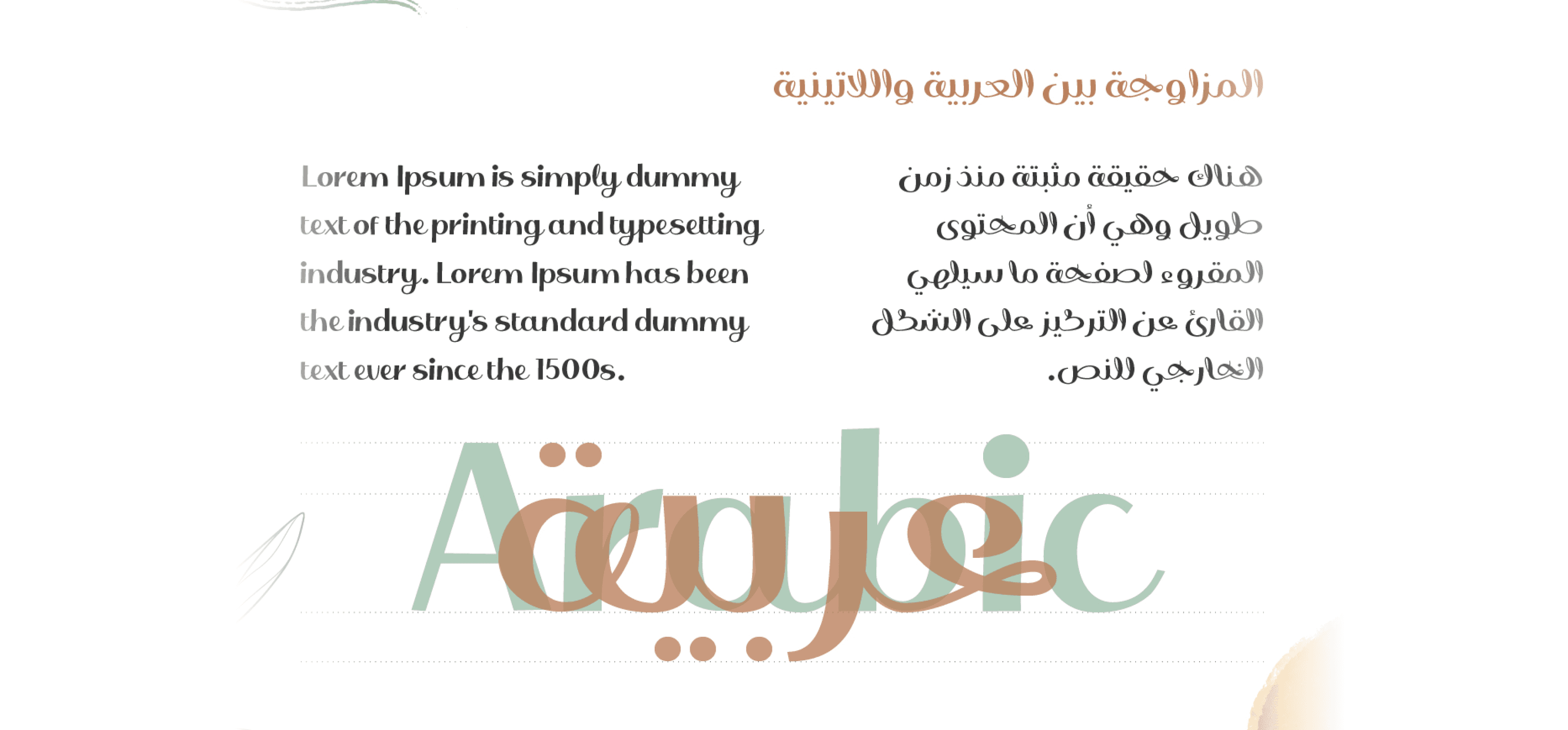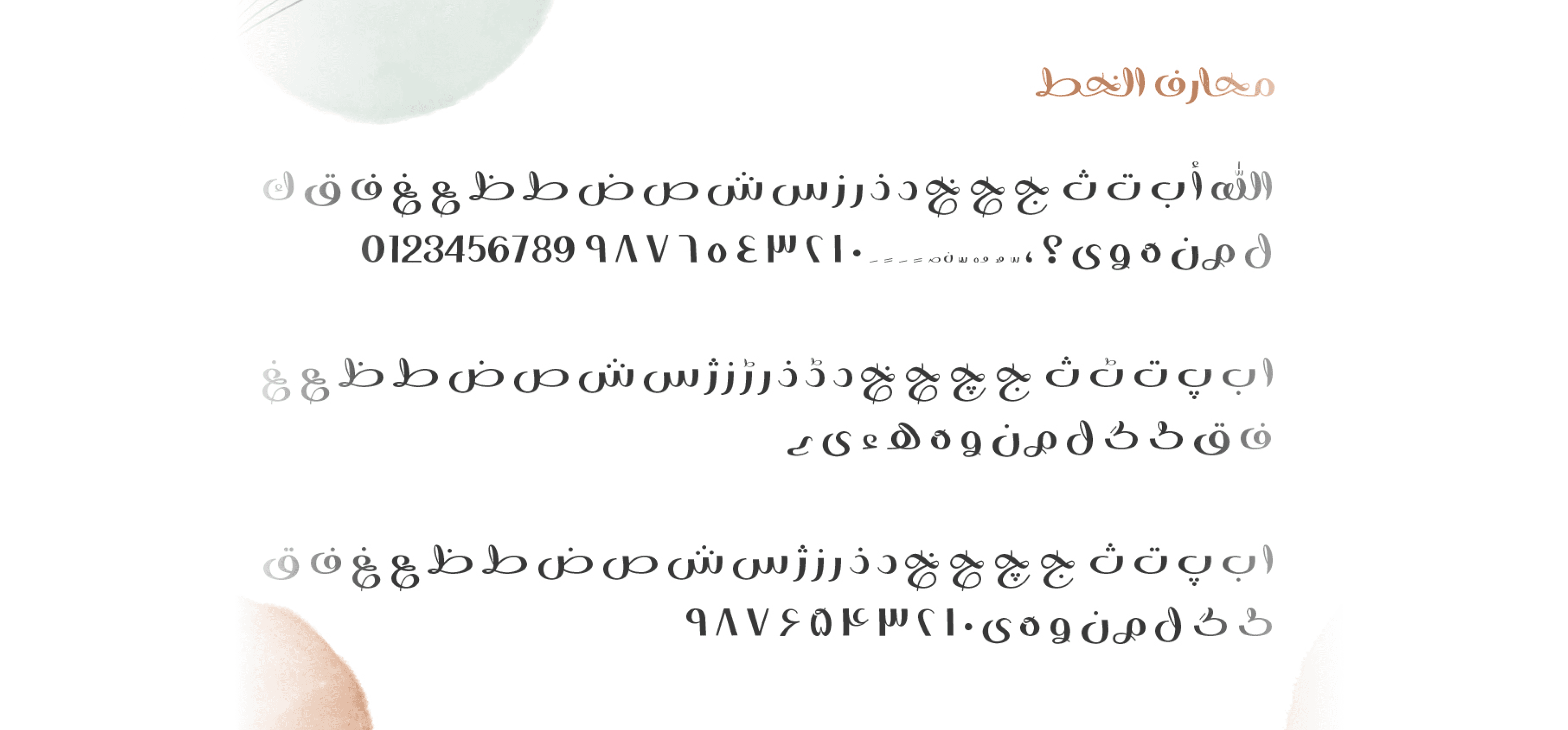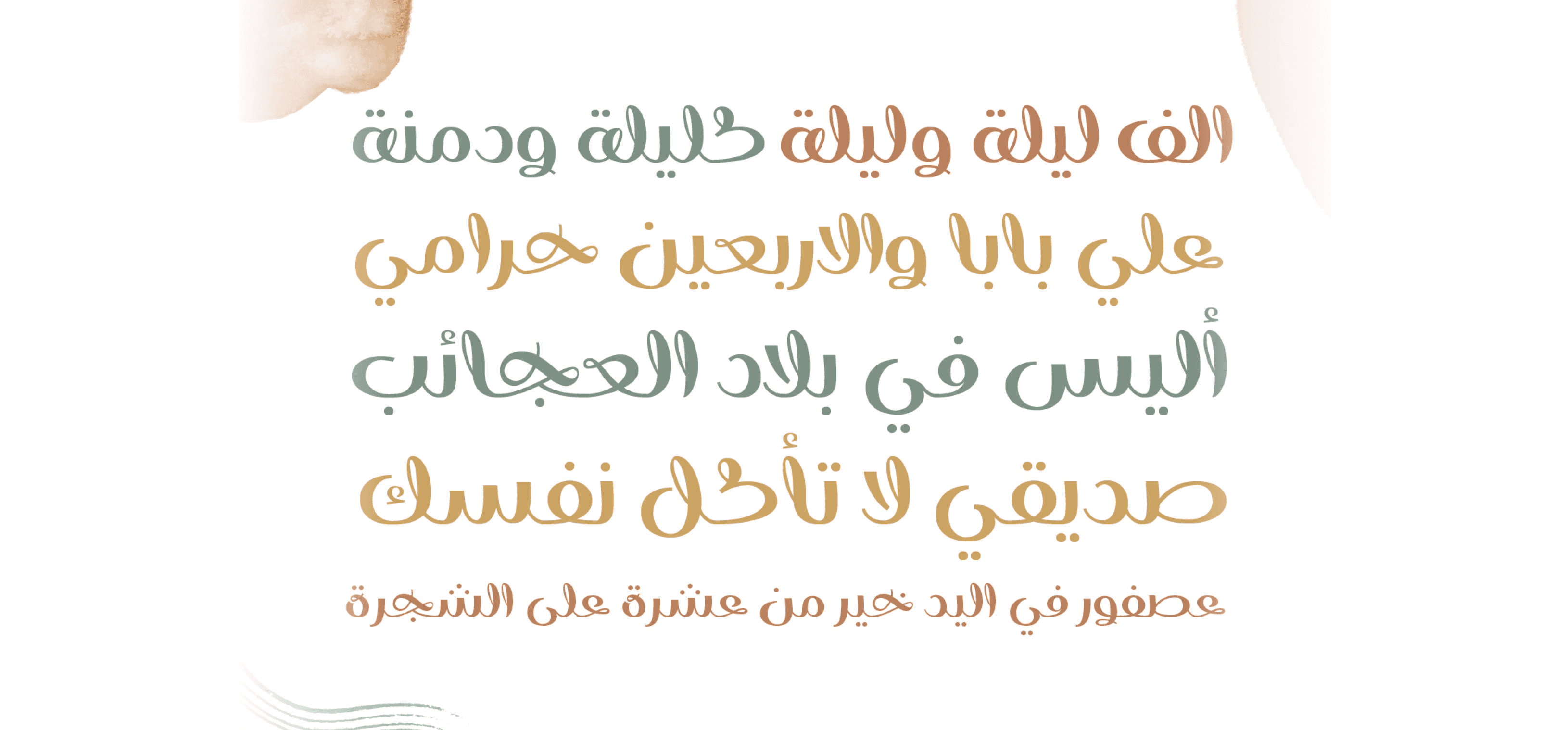
YR Gamila هو خط يدوي رائع يجمع بين الأناقة والحداثة. يتميز بمجموعة شاملة من الرموز الأساسية، تشمل الأحرف الكبيرة والصغيرة، الأرقام، والرموز، مما يجعله خيارًا مثاليًا للتصاميم التي تحتاج إلى لمسة شخصية وعصرية في آنٍ واحد.